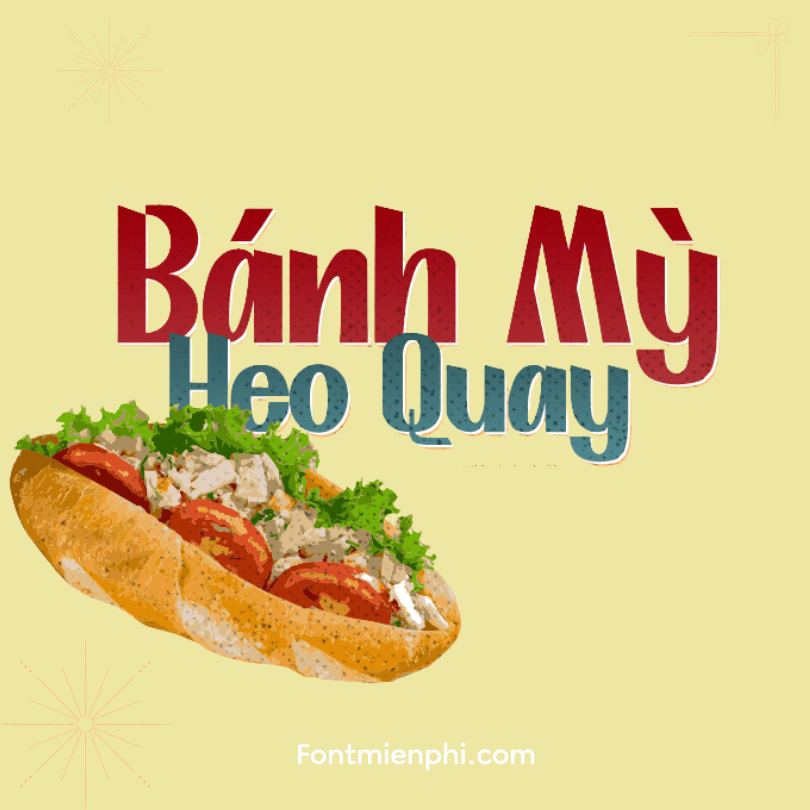
Việt hóa font 1FTV thiết kế ẩm thực 1
Việt hóa font 1FTV thiết kế ẩm thực 1 – Nét Chữ Đậm Đà Cho Thiết Kế Ẩm Thực
Font 1FTV Ẩm Thực 1 đã được Việt hóa hoàn chỉnh, là sự lựa chọn hoàn hảo cho các thiết kế ẩm thực đầy sáng tạo. Với nét chữ mập mạp, vui nhộn và đầy năng lượng, font mang đến hơi thở tươi mới cho:
• Menu nhà hàng, quán cafe
• Poster quảng cáo ẩm thực
• Thiết kế bao bì sản phẩm
• Banner khuyến mãi
Điểm nổi bật:
✔ Bộ ký tự đầy đủ tiếng Việt
✔ Nét chữ độc đáo, bắt mắt
✔ Dễ dàng ứng dụng trong nhiều chất liệu thiết kế